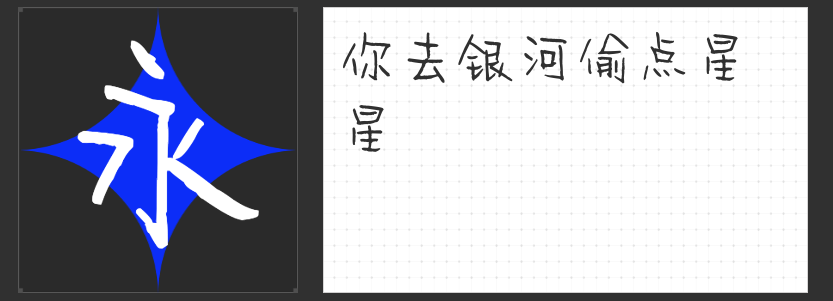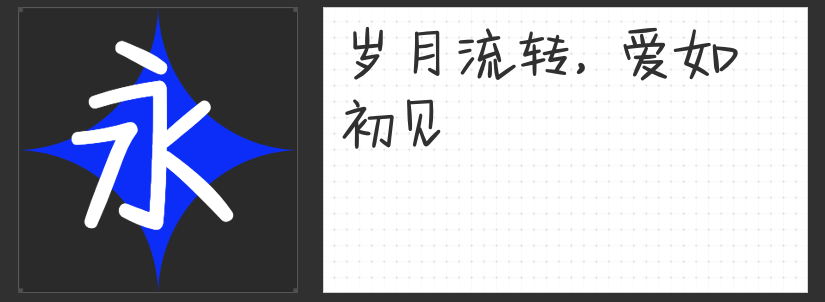
笔尖温度:四款手写感标题字体唤醒设计中的情感共鸣
在数字化浪潮中,手写字体以其独特的温度与个性,成为标题设计的灵魂之笔。以下四款各具风格的手写字体,既能传递真挚情感,又能为视觉呈现注入灵动气息,助您打破模板化设计的桎梏。
一、贴仔初恋体粗体
这款字体以情书字迹为灵感,将少女心事凝练于笔画之间。粗细适中的笔触既保留了手写的自然抖动,又通过工整的结构平衡了俏皮感。起笔处的圆润弧度与收尾时的利落顿挫形成微妙对比,仿佛能看见笔尖在纸面犹豫又坚定的轨迹。其独特的“不完美”特质,让标题在规整中透出呼吸感,特别适合需要传递温暖情感的设计场景。
二、字青春悸动简 常规
以端正字形为基底,这款字体通过笔画间的疏密节奏打破呆板印象。横竖撇捺的起承转合间暗藏书写者的从容姿态,转折处的细微弧度更添几分灵动。清秀而不单薄的视觉效果,使其既能驾驭短视频封面所需的视觉冲击力,又能在海报标题中保持优雅格调。适中的字重设计,让文字在不同背景上都能保持清晰可读性。
三、MyFont凌渡未卜简
当手绘的稚拙感遇上结构化设计,这款字体展现出独特的矛盾美学。略带倾斜的笔画方向与不规则的笔画粗细,营造出孩童涂鸦般的天真烂漫;而精心调整的字间距与重心平衡,又确保了多字排版时的和谐统一。其跨场景的适应性,源于对“可爱”的深度解构——既非刻意卖萌,亦不流于幼稚,而是以童真视角重构文字的视觉语言。
四、小豆岛默陌写意水墨简
这款字体将水墨书法的写意精神注入现代手写体系,飞白笔触与实线笔画交织出虚实相生的韵律。行笔时的速度变化被转化为可视化的线条粗细过渡,收笔处的墨韵氤氲则以数字化方式完美复现。传统与现代的碰撞,使其既能传递东方美学的含蓄意境,又符合当代审美对简洁形式的追求,尤其适合需要文化厚度的品牌视觉表达。
四款字体,四种笔触哲学。从青春悸动到童趣盎然,从水墨写意到清秀骨相,它们以不同的方式诠释着手写美学的当代价值,为设计师提供更多表达可能。